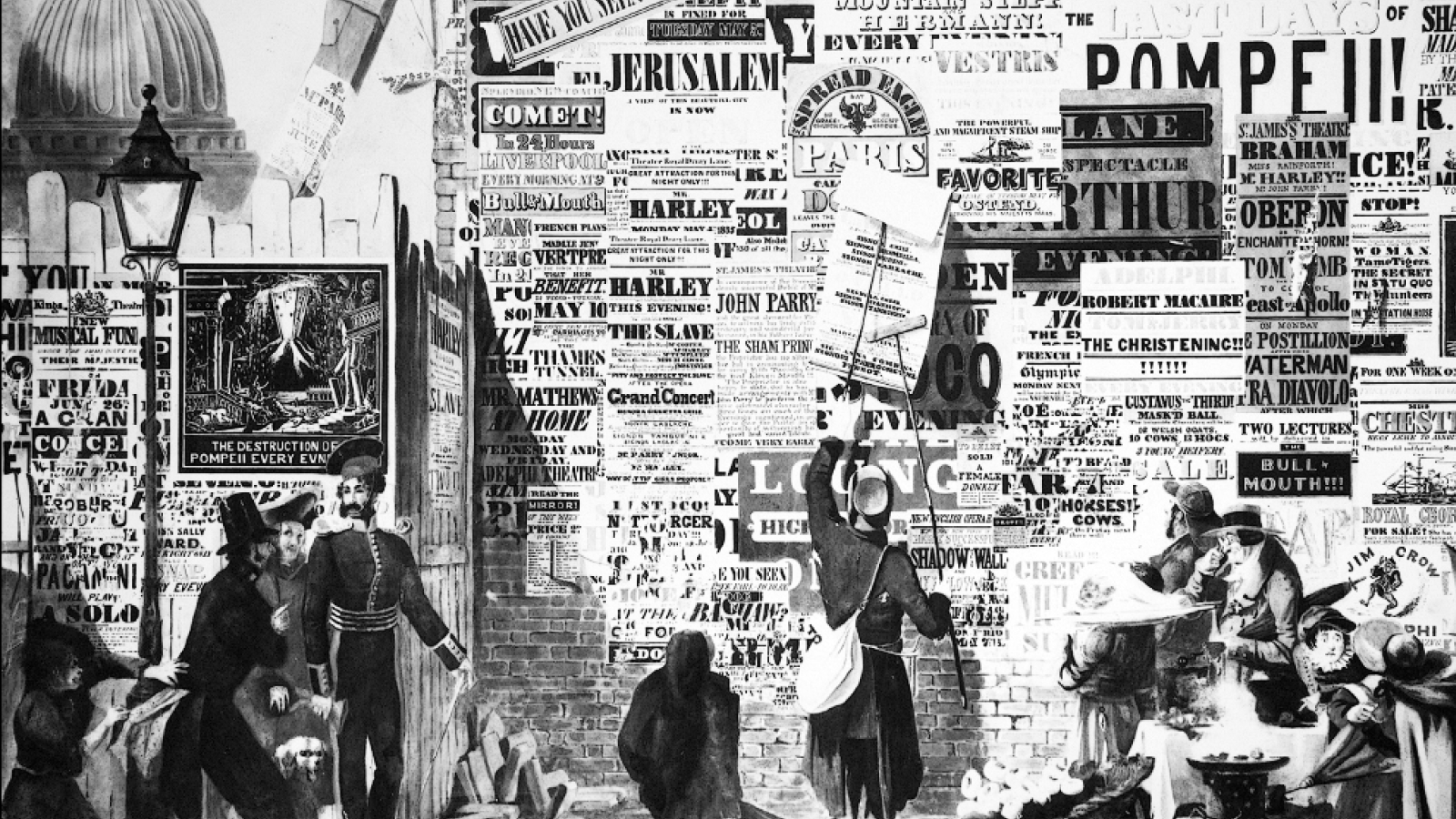
Шрифты и типографика Викторианского периода
19 век также называют эпохой «шрифтового взрыва» — в период промышленной революции возникло все разнообразие типов печатного шрифта. «Викторианский» стиль акцидентной типографики в наше время переживает настоящий ренессанс.
В прямом эфире дизайнер шрифтов Денис Машаров подробно и наглядно расскажет о типографике Викторианского периода, объяснит, как возникали различные шрифтовые классы, покажет эклектичные викторианские плакаты.